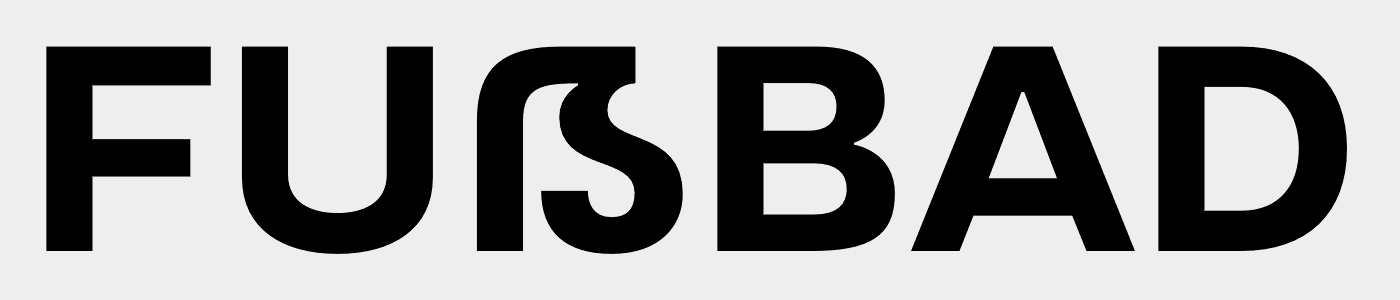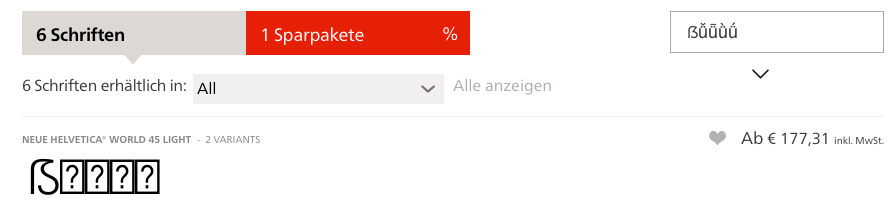
Die Neue Helvetica World steht Ihnen damit ab sofort in drei Strichstärken und zugehörigen sechs Schriftschnitten zur Auswahl: 45 Light, 55 Roman und 75 Bold, jeweils mit Italic. Die Sprachausstattung der Neue Helvetica World umfasst nicht nur den paneuropäischen Raum (erweitertes lateinisches Alphabet, Kyrillisch und Griechisch), sondern ermöglicht auch das Setzen von Arabisch, Hebräisch, Thailändisch, Armenisch, Georgisch und Vietnamesisch. Das kyrillische Alphabet beinhaltet nicht nur den üblichen Ausbau, sondern enthält den kompletten Unicode Block u+0400. Außerdem wurde die hebräische Sprachausstattung hinzugefügt. Mit einer Unterstützung von schlussendlich 181 Sprachen wird sie damit auch den komplexen Anforderungen von großen, internationalen Marken, Unternehmen, Verlagen sowie Software- und Hardware-Entwicklern gerecht.
Kann es wirklich sein, dass man trotz des umfangreichen Ausbaus mit über 1700 Glyphen pro Schnitt und Unterstützung von Kyrillisch, Griechisch, Arabisch, Hebräisch, Thailändisch, Armenisch, Georgisch und Vietnamesisch vergessen hat, ein deutsches Versal-Eszett aufzunehmen?
Also, ich glaube es ist drin ... aber dafür mal wieder kein Pinyin. Wozu auch, ist ja bloß die Transkription einer Sprache, die gerade mal ein Viertel der Weltbevölkerung spricht ...
Du hast in der Helvetica World nachgeschaut ... aber da ist es nicht drin, sondern in der (oben von dir ja auch verlinkten) Neuen Helvetica World.
Aber wenn es so missraten ist, isses auch fast schon wieder egal.
Übrigens fehlen auch die Glyphen, die man für die DIN- und ISO-konforme Transliteration arabischer, hebräischer und wahrscheinlich weiterer Schriftsysteme benötigt. Das ist ein Fehler, den viele Schriftgestalter machen. Dabei ist es doch so naheliegend, dass, wenn eine Schrift Lateinisch und Arabisch vereint, man auch die Transliteration arabischer Texte immer mal wieder schreiben muss. Und IPA fehlt auch. Na ja, tolle »Weltschrift«!
Also ich finde diese Form schon eigenwillig, in kleinen Gerade problematisch und für so ein Arbeitstier wie die Helvetica letztendlich denkbar schlecht geeignet. Ist es ein Zufall, dass Schriftgestalter, die sich ausgiebig mit dem ẞ beschäftigt haben, die Form so gut wie nie wählen?
Seht ihr das anders?
missraten*
und
eigenwillig**
sind bei mir halt zwei paar Schuh. :tutor:  ;-) :-?Aber ich verstehe was Du meinst. :-)
*Als Versaleszett-Form gar nicht zu gebrauchen, da unter anderem mit ß oder B verwechselbar bzw. als gar kein Buchstabe erkennbar.
Zum Beispiel:
**Eine der üblichen ẞ-Formen als Grundlage, aber in Proportionen etc. ungünstig oder von den Sehgewohnheiten leicht abweichend gezeichnet.
Zum Beispiel:
Ich meine schon dasselbe. Nur halt einmal auf 🇩‍🇪 und einmal auf 🇺‍🇸. 8-)
Klar ist das ẞ hier nicht missraten im Sinne von formal falsch. Allerdings kann ich mir keine Anwendung vorstellen, bei der einerseits die neutrale Helvetica passen, anderseits solch ein ausgefallenes ẞ nicht stören würde.
Man muss es wahrscheinlich auch mal im »Zusammenhang« betrachten.
Mehr statische Groteskschriften mit ẞ bei Myfonts fallen mir gerade nicht ein.
Ich glaube ich finde das ẞ der Helvetica für diese Gattung auf jeden Fall stimmiger als die bei der Applied Sans gewählten Form. Schon allein deshalb würde ich nicht von missraten sprechen.
Tja, das müsste man mal in echten Anwendungen sehen. Vielleicht würde ich mich dann daran gewöhnen. Ich kann mich jedenfalls an keine Anwendung dieser Form erinnern, die mir schon mal über den Weg gelaufen wäre, während die Haas-Form heute schon fast allgegenwärtig ist.
Mir steht das dynamische Zurückschwingen beim ẞ der (Neuen) Helvetica zu sehr im Kontrast zur Statik der Schrift an sich.
(Bei der Travels und noch mehr bei der Aktiv ist das passender gelöst, wenngleich ich für diese "klassischen" Groteskschriften die Form an sich problematisch finde.)
Vielleicht kommt die Diskrepanz auch daher, weil wir unterschiedliche Betriebssysteme nutzen. :-)
Gut möglich, wobei ich eher so an Real-Life-Anwendungen gedacht hatte. Seht ihr da das Helvetica-ẞ?
Sind die bei der neuen Helvetica Now dabei? Die habe ich heute bei MyFonts gesehen (https://www.myfonts.com/fonts/mti/helvetica-now/) und zumindest das Versal-Eszett passt ja jetzt viel besser. Reizvoll sind sicher auch ein paar andere Neuerungen (eigene Schnitte für Text-, Display- und kleine Größen sowie Alternativformen für einige Glyphen).